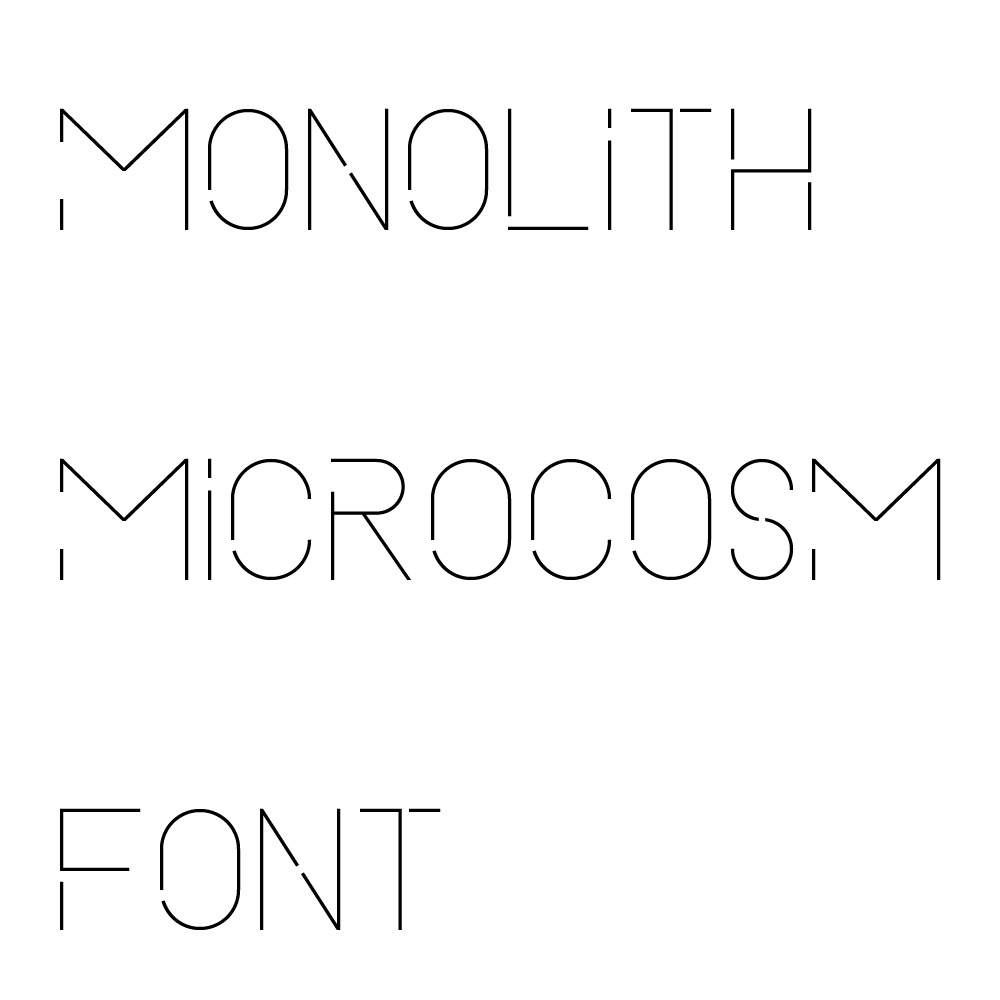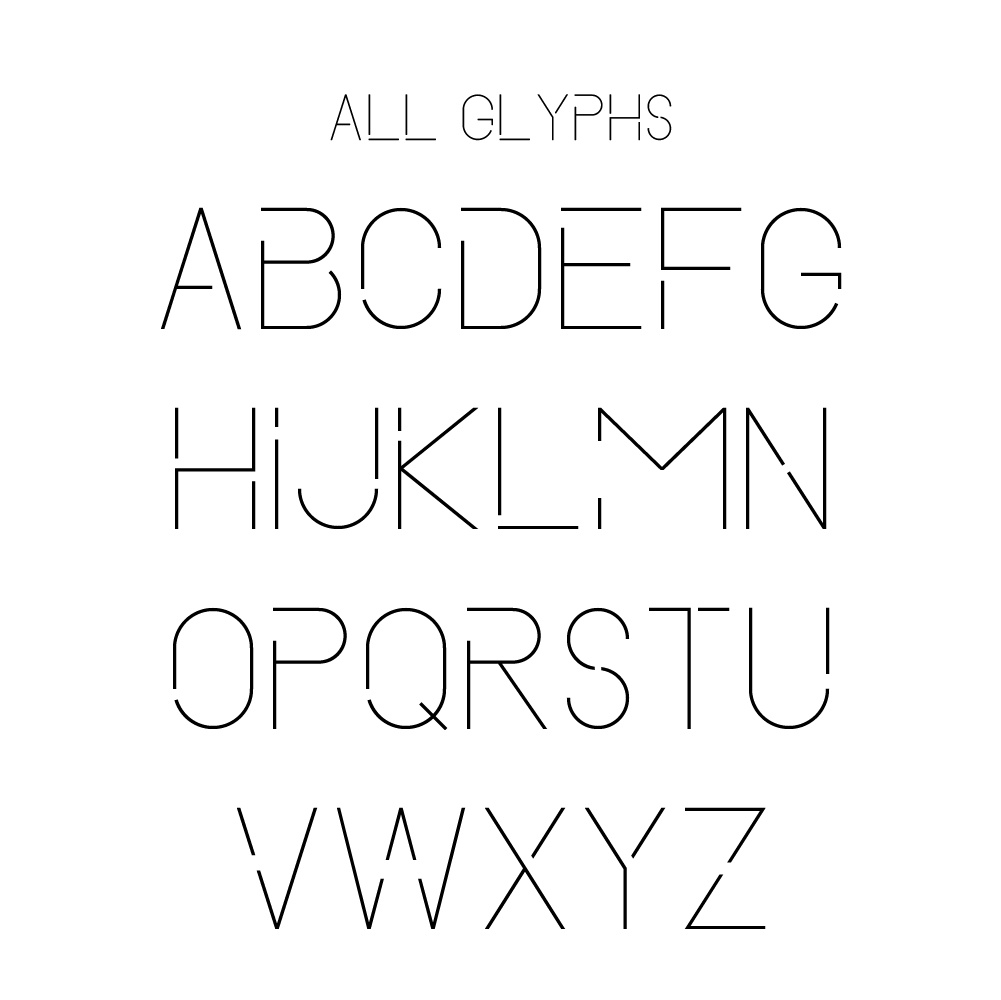
オリジナルフォント「Microcosm」
線を極限まで細くし、ところどころ途切れさせた欧文ディスプレイ書体です。 Microcosm(日本語訳: 小宇宙)と名付けた理由は、宇宙のように美しい(?)フォントにしたかったからです。 ロゴ、タイトル、パッケージなど、大きなサイズで組むことを想定して設計しています。
収録内容
・大文字 A-Z(26字) ・半角スペース ※ 小文字キー(a-z)を打っても、同じ大文字の字形が出ます。 ※ 数字・約物(記号)・かな・漢字は収録していません。 これらを入力した場合、文字は表示されません。